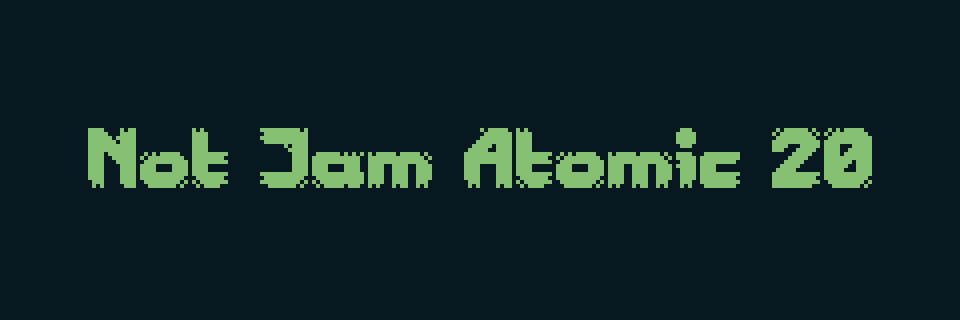
Шрифт «Not Jam Atomic 20»
По лицензии Creative Commons Zero v1.0 Universal для свободного скачивания предлагается шрифт «Not Jam Atomic 20». Это гранжевый пиксельный шрифт, во многом вдохновленный шрифтом из «Nuclear Throne». Он имеет высоту 20 пикселей и доступен для использования в любых коммерческих и некоммерческих проектах без ограничений. Пригодится при разработке ваших игр.